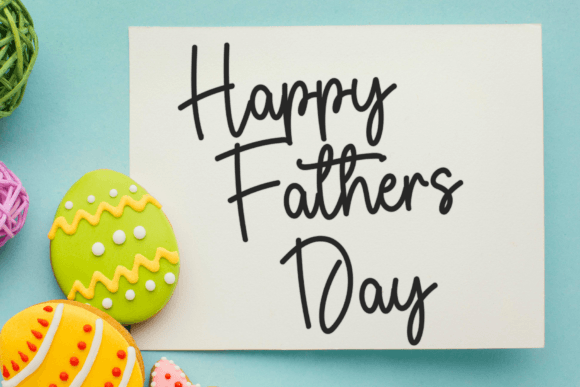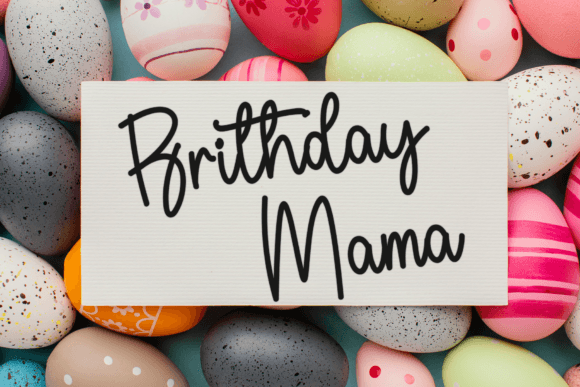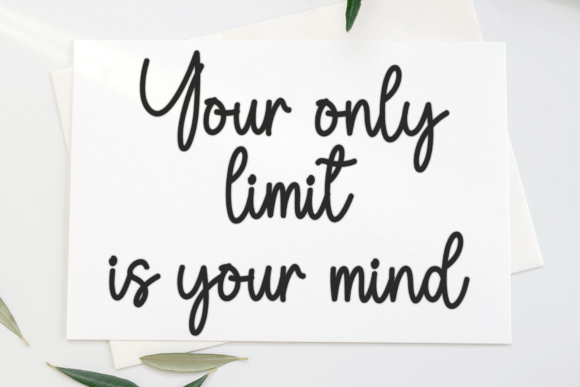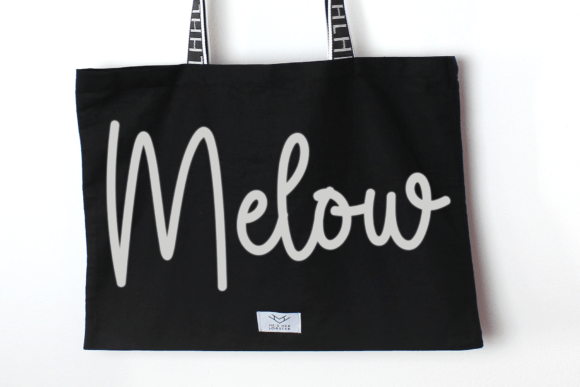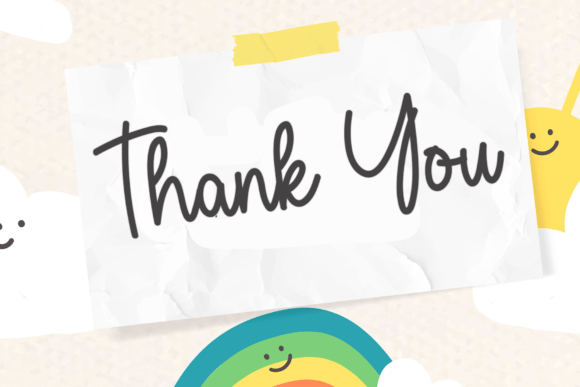
فونت Mothers Day انگلیسی
دانلود فونت Mothers Day انگلیسی Font مادرز دی |
| ⭐ مجموعه فونت | دانلود فونت انگلیسی روز مادران Font Mothers Day |
| ⭐ توضیحات | فونت روز مادر را معرفی می کنیم، خطی دلپذیر و لطیف و حروف دست نویس که عشق و گرمای مادری را جشن می گیرد. این فونت با منحنی های ملایم و حروف برازنده خود، جوهر عاطفه مادری را به تصویر می کشد.
فونت روز مادر که برای کارتهای روز مادر، پیامهای صمیمانه و پروژههای شخصی ایدهآل است، حسی از عشق و قدردانی را اضافه میکند و احساسات صمیمانه را با هر ضربه منتقل میکند. |